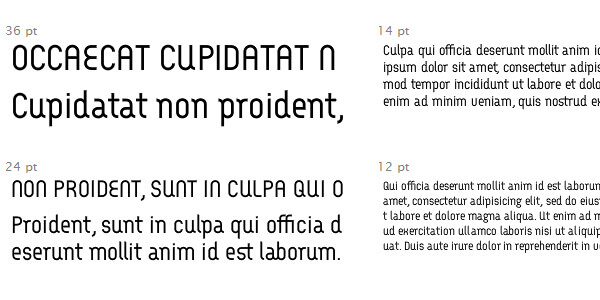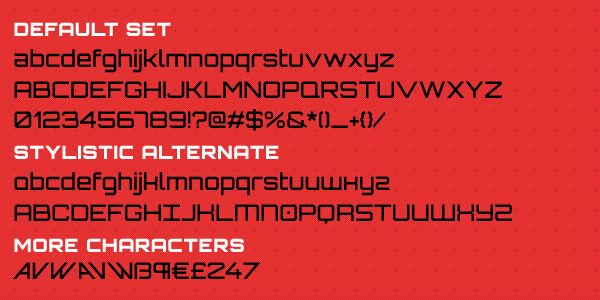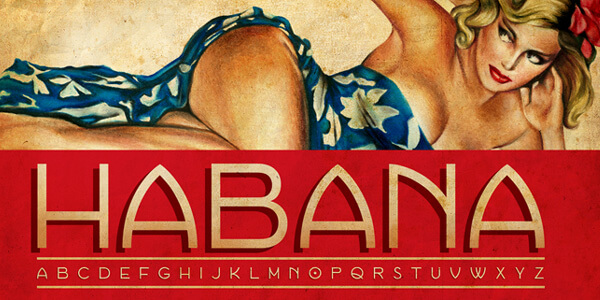
グラフィックデザインないしウェブデザインでは、顧客やビジターにメッセージを伝えるためにタイポグラフィーを使用しています。フォントとは、コミュニケーションのために用いられる文字の種類であるとされます。電子出版の分野においては、コンピューターの画面でも読みやすく理解しやすいサンセリフ体が最も一般的であり、文字の最後に装飾がないため、しばしば見出しに利用されます。また、このフォントはジオメトリック、ヒューマニスト、グロテスク、ネオグロテスクに分類できます。
ジオメトリック・サンセリフにはSpartanやFutura、Century Gothic、ITC Avant Gardeが含まれます。名前が示す通り幾何学的な形態を持ち、エレガントでモダンな印象を与えます。このため現代的なデザインプロジェクトの表題に広く用いられる一方で、本文としてはあまり用いられません。サンセリフ体にはオンラインで入手できるものもいくつかあり、その中からプロジェクトのために最適なものを探して選ぶこともできるでしょう。解像度の低いコンピュータでも判読しやすいことから、しばしばウェブデザインにも用いられます。
あまりフォーマルでないカジュアルなルックスを求めているのなら、あるいは短いテキストが手元にあるのなら、ジオメトリック・サンセリフをおすすめします。独特の視覚的な魅力と典型的な黒色によって、コンピュータを利用する人々に人気を博しています。ウェブデザイナーはまず、ウェブデザインにおけるタイポグラフィーの役割と用途について理解する必要があります。何の変哲もない作品であっても、適切なタイポグラフィーを用いることで素晴らしく魅力的に見せることができるのです。取引先や顧客の要求に応じてフォントを選ぶと良いでしょう。
ブランド名や会社のロゴに与えられているフォントの正しさは、視覚的な様相と企業のアイデンティティに大きく依存するということを、いつも頭に入れておいてください。これらのフォントは専門性と明快さにひいでており、エレガントでモダンな見た目でビジターを魅了します。ウェブサイトの親しみやすさを高め、コンテンツに適したフォントを選択することを大切にしましょう。
Habana
Habanaはキューバのテイストとピンナップにインスパイアされた、美しく洗練されたフォントです。わずかな影によって生じる立体感が特徴的で、タイトルや見出しに適しています。英語やドイツ語などのラテン系の言語に対応しています。
Orbitron
Orbitronは楕円形をベースに制作されたなめらかで幾何学的な形体を持ち、高級感があります。以下が用意されています。
・英語に固有の文字は大文字と小文字の両方で表示
・数字
・基本的な句読点
・スタイル代替
・タイトルにスパイスを加えるための特別な装飾的グリフ
Walkway
Walkwayはデリケートでなめらかな線で構成された、エレガントで繊細なフォントです。この現代的なフォントは、以下を含んでいます。
・およそ10種類のスタイル(Semi-Bold RegularからBold Italicまで)
・200個以上のグリフ
・フランス語、スウェーデン語、オランダ語、スペイン語などの幅広い言語に対応
Waukegan LDO
カジュアルかつエレガントなサンセット体のWaukegan LDOは、10年前にLuke Owensによって制作されたフォントで、タイトルの装飾やテキストの細部への強調といった多くの目的に適しています。
通常のタイトなメトリクスから、extended boldのルーズなメトリクスで終わるスタイルが1ダース、そして大文字と小文字のアルファベット、数字、基本的な句読点を含む227個のグリフがあります。
Arcus
Arcusはギリシャ風のフォントでうるさくなく、あらゆるタイトルないしテキストに地中海沿岸の愛らしさを与えてくれます。装飾的なフィニッシィングストによって美化された各はカリスマ性を感じさせます。このような華やかな見た目にも関わらず、最小サイズを含むどのサイズでも明快に見えます。標準的なバージョンを入手して、このフォントの素晴らしさを楽しんでください。
edelsans
Edelsans は極細の線ないし円によって形成されている典型的なフォントです。わずかに68個の基本的なグリフと少数のエクステンデッドセットが存在し、英語とその他のラテン文字のためにデザインされています。そのほかには、シンタックスの向上のために数字と記号が含まれています。
Giro
一流の幾何学フォントであるGiroは、セリフの省略と丸い形体が魅力です。音楽的で力強いエネルギーを感じさせるフォントで、シンプルに洗練されたLightと、縁取りによってアーティスティックな雰囲気を感じさせるNormalの、2つのオプションがあります。
Acid
Acidには6つのオプション(Regular、Regular Italic、Medium、Medium Italic、 Bold Italic)があります。グリフは103個のみ(ラテン文字とスモールエクステンデッドセット)であるため、使用は制限されます。少し曲がったなめらかな線が目を楽しませてくれます。
Metrophobic
MetrophobicはNormalのみですが、パラグラフおよびタイトルのどちらにも対応可能です。さらにグリフのカバレッジはとても広く、句読点や代替文字を含むおおよそ300個の記号が存在しており、西および中央ヨーロッパの様々な言語に対応します。
Code
The codeは読みやすさを念頭に置いて制作されたフォントで、間違いなくプロジェクトや作品の可読性を次の段階へすすめてくれます。判読のしやすさはサイズの大小に左右されず、カジュアルなハイテク感のある、清潔でシャープな形体が魅力的です。
Singula Compressed
Singula Compressedは本記事では2つ目の極細のフォントで、エレガントな繊細さを持っています。この独特のフォントでは多数の代替記号、OpenType機能、そして基本的なグリフの使用が可能です。利用は非営利目的に限られ、それ以外の目的のために使用したい場合には制作者に連絡する必要があります。
Champagne & Limousines
Lauren Thompson制作のChampagne & Limousinesはラグジュアリーでシックの印象のフォントで、あらゆるエレガントでなめらかなUIに調和します。一般的なTTF形式で利用でき、以下の要素を備えています。
・4つのスタイル(Normal、Italic、Bold、Bold Italic)
・代替ないし記号のエクステンデッドセットを含む多数のグリフ
Faucet
Faucetはすこしテクノでデジタルな雰囲気が特徴的です。基本的な幾何学形態と文字と文字との間隔の適当な使用を示しています。残念なことに、このフォントはロマンス語のみにしか対応していないのですが、シンタックスのための数字やたくさんの記号が用意されています。タイトルを目立たせるための使用がおすすめです。
LT Oksana
LT Oksanaはフェミニンなタッチと愛らしい手書きの魅力のフォントで、おしゃれで繊細なデザインにぴったりでしょう。円形と楕円形、そしてなめらかなエッジをベースとしており、以下の要素を備えています。
・4つのスタイル(Normal、Italic、Bold、Bold Italic)
・多くの言語に対応するたくさんのグリフ
Geometry Soft
Geometry Soft はなめらかな形態を優先的に用いることで、多くの幾何学的なフォントに見られる角張った形態を巧みに回避しています。太字のオプションとして優れた機能を果たし、様々なヨーロッパ言語に対応するあらゆるグリフ備えています。合字やスモールキャップス、スタイル代替やエクステンデッドセットのようなOpenTypeのバリエーションを備えているので、見出しやコピーに使用が容易でしょう。
Digital Serial
Digital Serial はハイレベルな繊細さと洗練を示しているフォントで、7つのスタイルの整然としたエレガントな形態が特徴です。無料で利用できるのはデモ版のみで、このバージョンはこのフォントの使用感を知るのに不可欠な要素のみが用意されています。
Michroma
Vernon Adams 制作のMichroma は独特のハイテクは印象とビジネスライクな落ち着きのあるフォントとして分類されます。スタイルはRegular一種類のみですが、460個と大文字と小文字の代替セットを備えており、フリーミアム製品としては感動的です。ラテン文字に基づく言語に対応しています。
Ribbon
Ribbonは太く目を引くカリスマ的な雰囲気を持ち、アーティスティックな見出しへの使用がおすすめです。この手の込んだフォントによって、あなたの伝えたいことに注意をひくことができるでしょう。また以下の要素を備えています。
・必須の文字
・数字
・様々な言語に対応したOpenType機能
・中括弧やクスクラメーションマークなど、一部の句読点
Raleway
Matt McInerney制作のRalewaは、とても細く、軽やかで美しいニューグロテスクのフォントです。多数のグリフのカバレッジを有しており、以下の要素が含まれています。
・オールドスタイル数字とライニング数字
・欧文合字ないし任意の合字
・ダイアクリティカルマーク
・スタイル代替
太さは細身のもののみですが、それでも十分に利点を引き出すことができるはずです。
フォントでプロジェクトをより魅力的に
ジオメトリック・サンセリフ体のフォントは標準的な形態から構成されたものですが、鋭い角張りや単純さはまったく感じられず、むしろシックで柔らかな優雅さをたたえ、なかには空想的で込み入った印象のものもあります。こうした魅力には普遍的な豊かさがあり、同時にそしてハイテクな雰囲気、フェミニンでアーティスティックな感覚を調和させています。このフォントを使用することで、たくさんのプロジェクトを魅力的なものにできるでしょう。